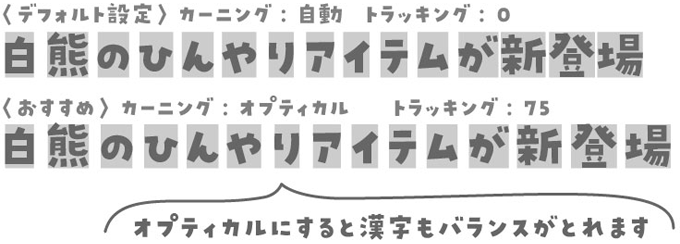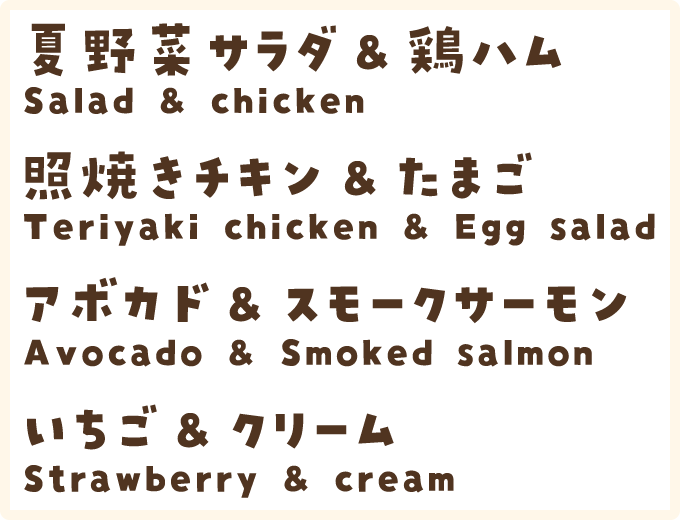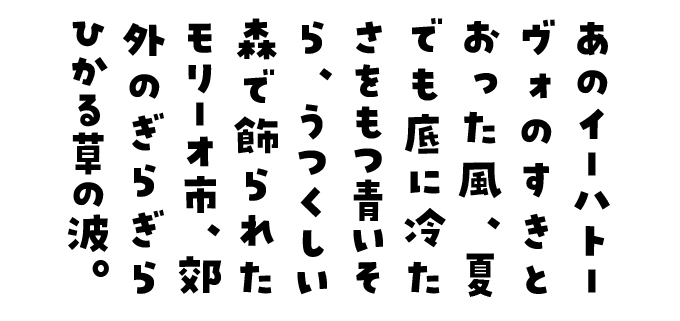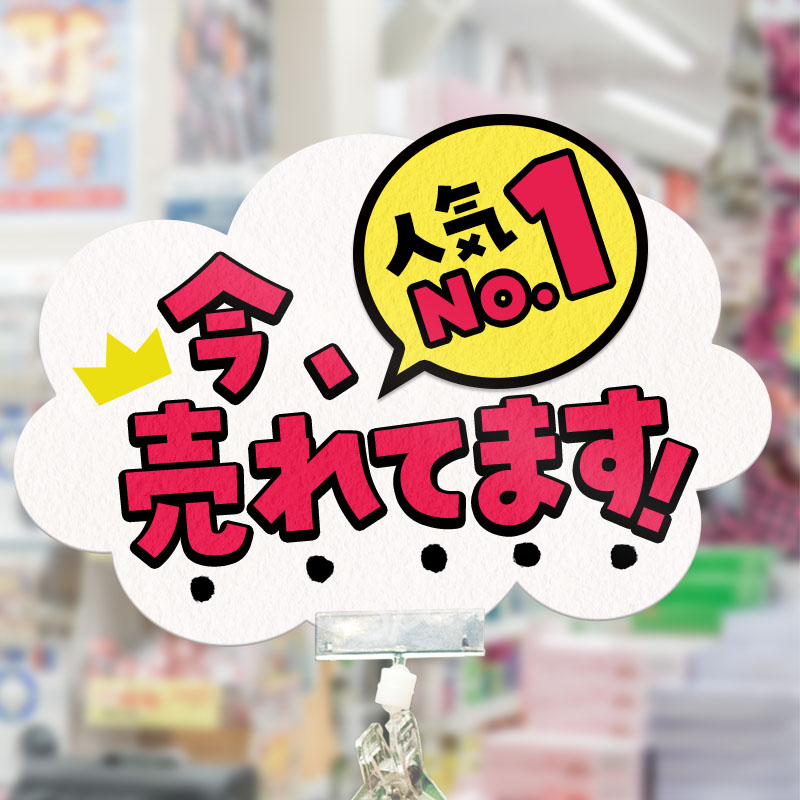
2018年秋の発売以来、SNSでも話題の大人気フォントです。手描きのような自然なリズム感と、見出しやパッケージにも最適なしっかりとした太さ。そして何より手作り感のある可愛らしさ。
太めの手書き風ゴシック系日本語フォント
ひらがな・カタカナ・アルファベット・数字・一部の記号・一部の縦書き文字・漢字 (JIS第一水準・JIS第二水準・IBM拡張漢字)
パンダベーカリーの文字サンプル
パンダベーカリーのひみつ
その1.手書き文字のようなリズム感
ひらがな・カタカナ・数字はぎゅっと小さめに、半濁点は大きく、でこぼこした並びでリズミカルになります。
その2.かな文字はプロポーショナル
見出しなどで漢字が詰まって気になるときは、Adobe Illustratorなどでカーニングをオプティカルにしてから、トラッキング数値を広めにして使うのがおすすめです。
こんな用途におすすめ
料理やDIYなど手作り感を出したいジャンルに
絵本や児童書、学習教材、イベントに
ゆるっと・かわいく・ほのぼの・まじめに・漫画風・話し言葉に
パンダベーカリーの仕様
漢字もたっぷり、約6,700字入り
第一水準、第二水準、IBM拡張漢字を収録。日常で使う文字はほぼカバー出来ます。
第二水準漢字の苺・珈琲・贅沢など使用頻度が高いものも空白にならずに表示できます。
新スタンダードのJIS2004字形で収録しています
デザイン書体ではまだちょっと珍しい、JIS2004字形を採用しています。収録は第2水準漢字まで。
縦書きにも対応しています